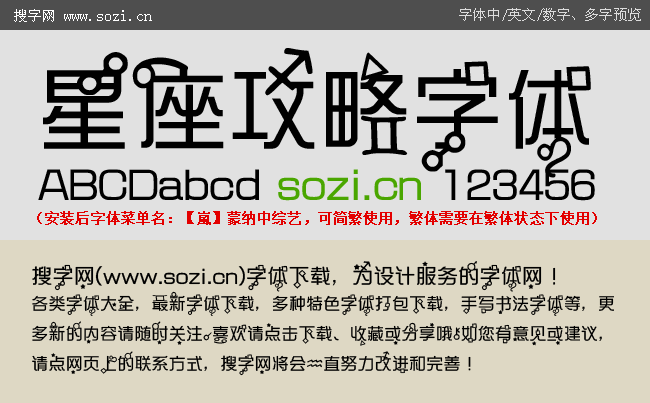
星座攻略字體
搜字網(wǎng)給大家提供一款很有趣的手機(jī)中文字體下載。修改者將它命名為星座攻略字體,這款手機(jī)字體是以蒙納中綜藝為原形,字體間裝飾了一些非常有趣的卡通圖案,搜字網(wǎng)為大家提供一款蒙納簡中綜藝體下載,蒙納簡中綜藝是一款用于設(shè)計(jì)方面的中文簡體漢字,時(shí)尚高雅、高端大氣,特別適合喜歡手機(jī)字體個(gè)性一些的朋友在手機(jī)上安裝使用。